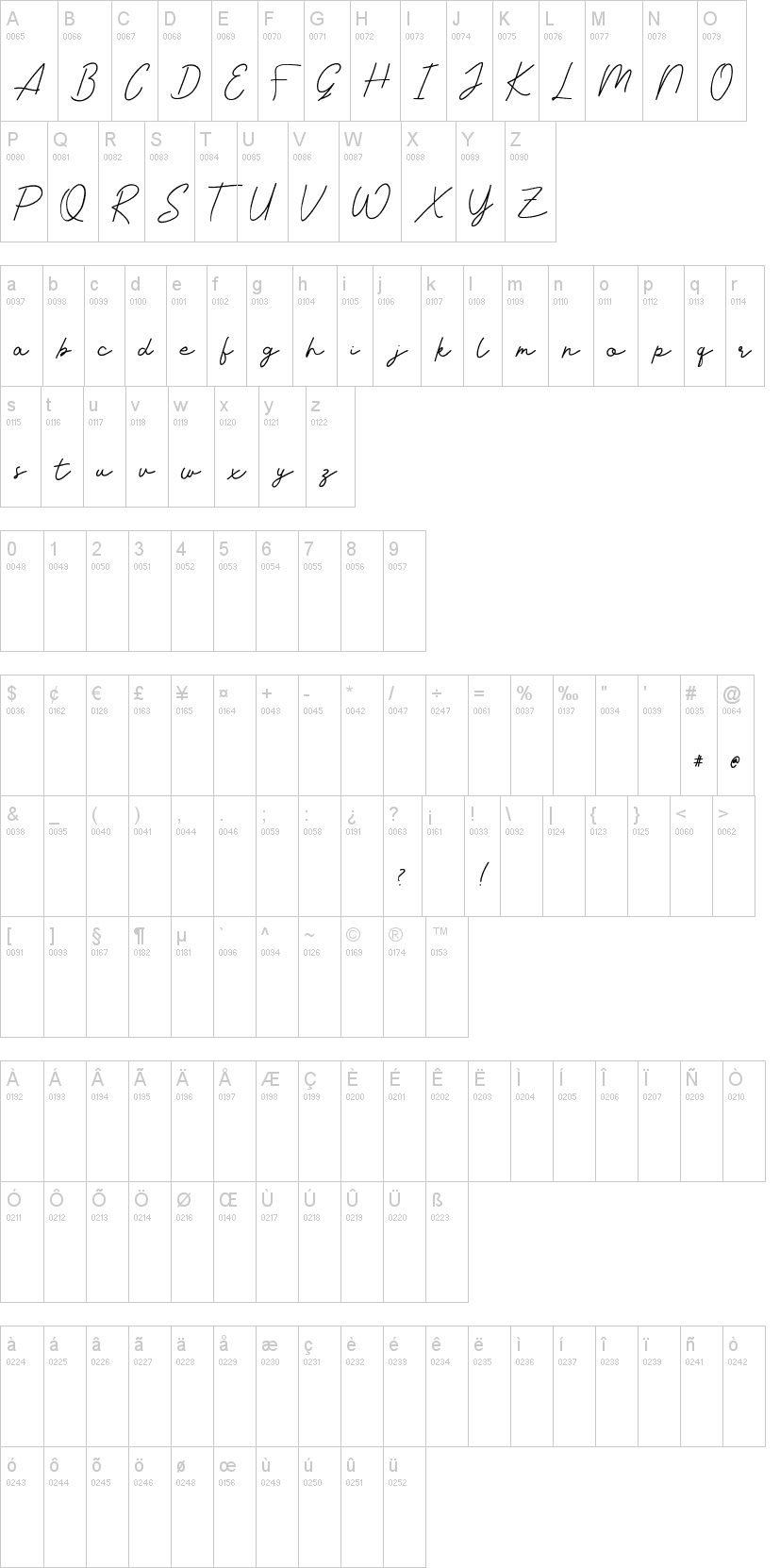
Livvie Signature
Livvie Signature 是一种手写风格的字体,由字体设计师 Mikrojihad 创造。这种字体的设计灵感来自于自然、优雅、浪漫的氛围。 Livvie Signature 字体具有流畅的笔画和优美的曲线,适合用于手写信件、卡片、海报、标志等设计项目中。它的特点是每个字母都有一些装饰性的附加元素,如曲线、划线等,使得整个字体看起来更加美观。 此外,Livvie Signature 字体也有一些变体,如 Livvie Signature Light、Livvie Signature Bold 等,可以根据不同的设计需求选择不同的字体变体。它可以适用于许多不同的设计项目,从个人品牌到商业项目,都可以使用 Livvie Signature 字体来增加设计的个性和美感。
Livvie Signature是一款非常不错的手写艺术字体,具有很好的视觉感,适合于文化类的宣传设计、商业类品牌的广告和产品包装设计以及个性化文字排版等较多场景。